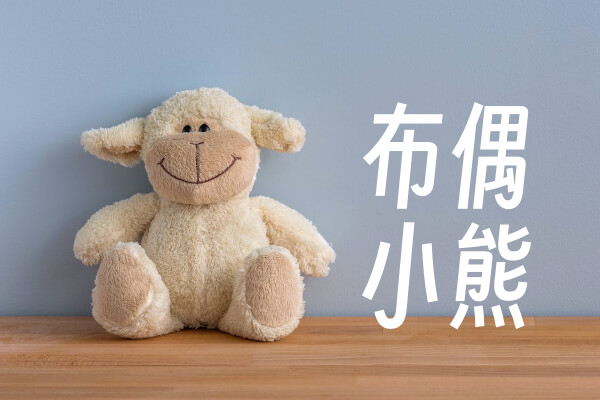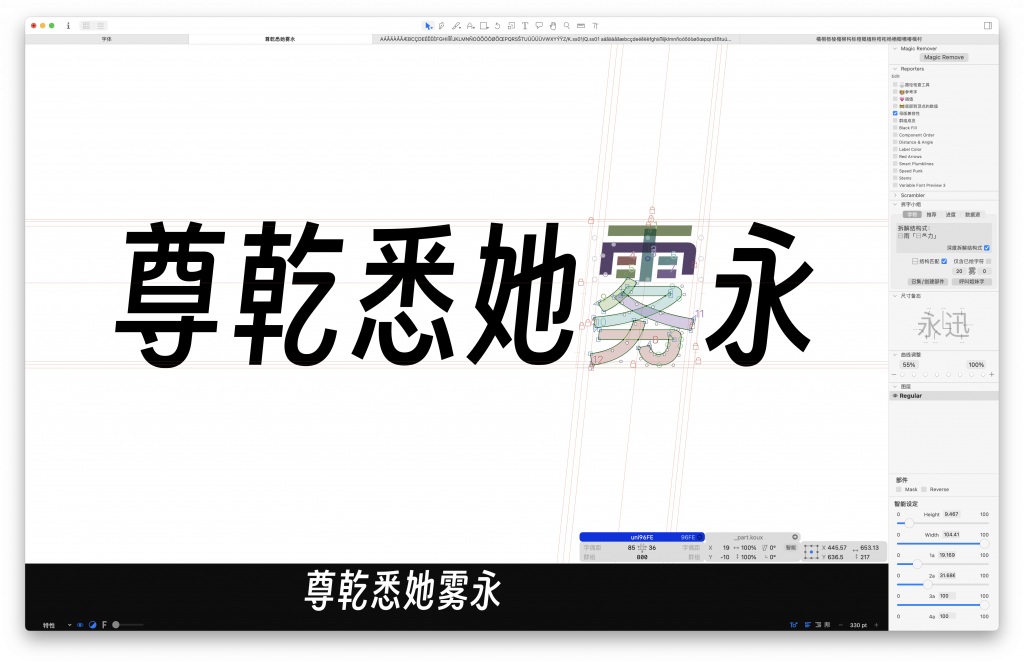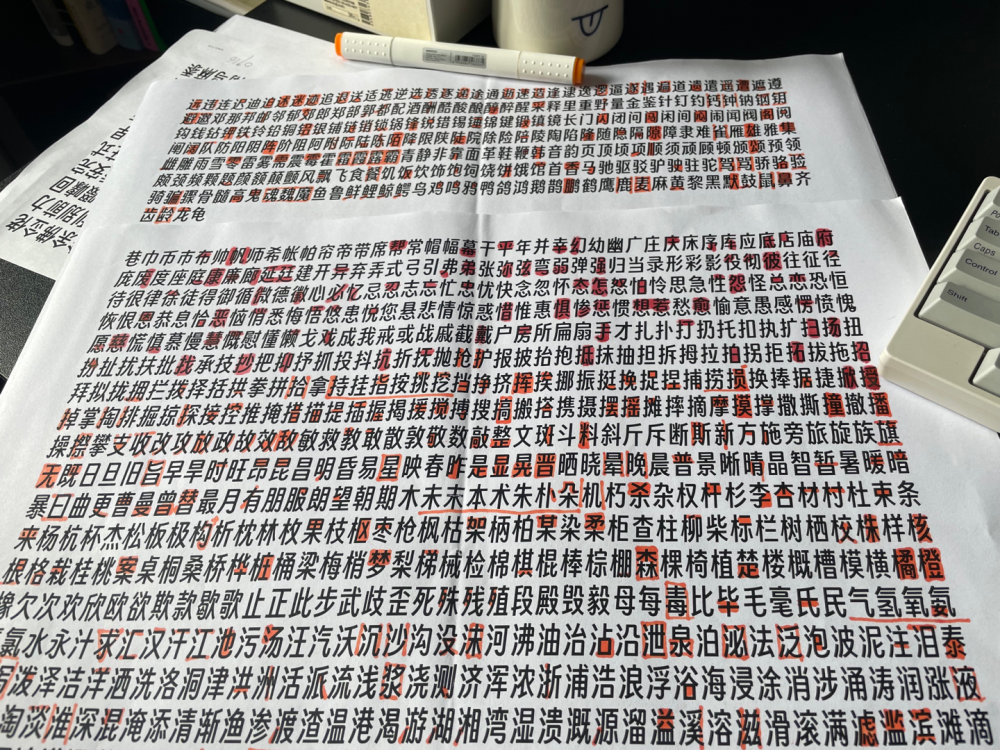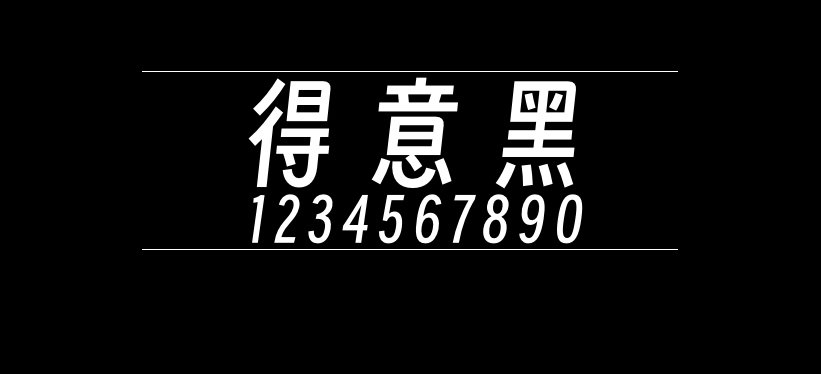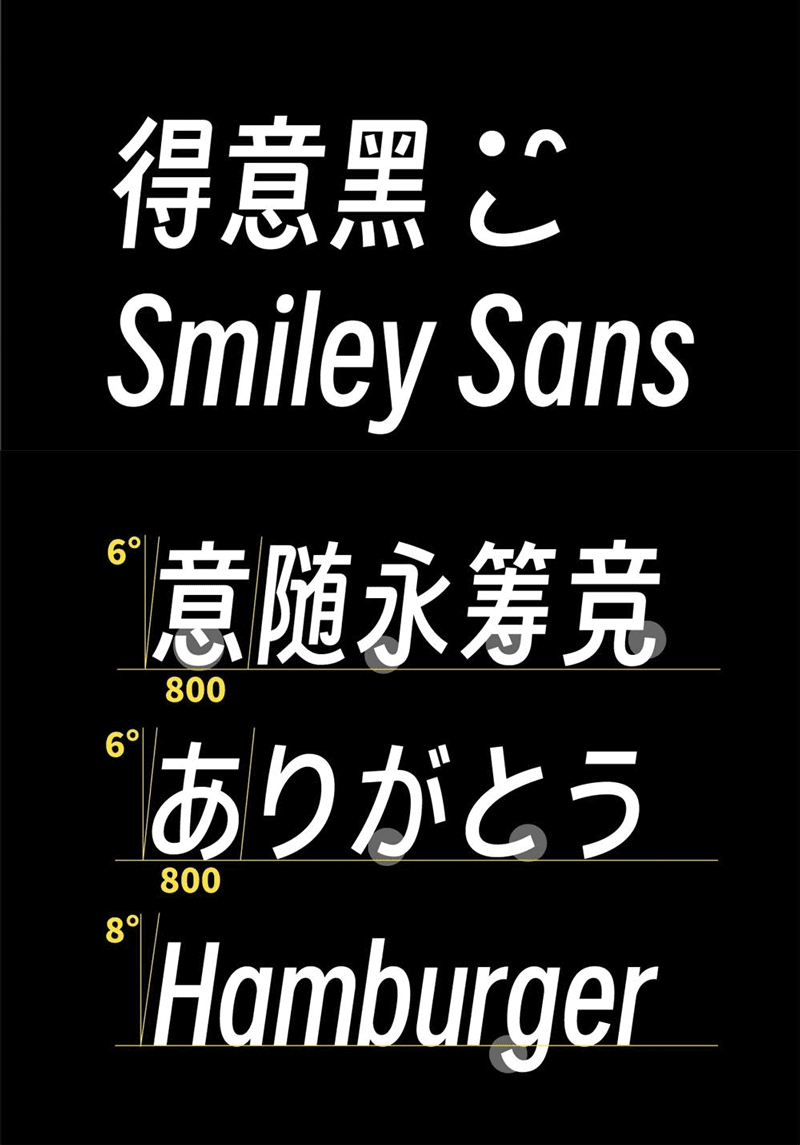
得意黑
得意黑(Smiley Sans)是oooooohmygosh发布的第一款字体,11月15日正式开源发布,大家可以免费商用无任何限制,也可以修改创作。作者希望以这个身份发布的所有作品,都是开源或者公益的。 这套字经过作者和其他字体设计师伙伴们一年多的波折,终于要面世了。据作者介绍,这款字虽然是美术字,但却是一个有挑战的命题。因为它有三个特征「大弧线、窄、斜」,每一项都很难做好。更何况把它们仨融合到了一起,还要去追求稳、匀、整……
得意黑是一款在人文观感和几何特征中寻找平衡的中文黑体。整体字身窄而斜,细节融入了取法手绘美术字的特殊造型。字体支持简体中文常用字(覆盖 GB 2312 编码字符集)、拉丁字母、日文假名、阿拉伯数字和各类标点符号。
字符集支持
汉字(中国大陆)
字体覆盖 GB 2312 编码字符集中的全部 6763 个汉字,并额外补充了 啰、喰、瞭、 4 个字,共计支持汉字 6767 个。
拉丁字母
除基础拉丁字母外,覆盖欧洲、美洲、南亚各种语言所需的字符共 415 个,另加入必要的变体和本地化字形,可支持 100 余种语言,包括英语、法语、德语、西班牙语、芬兰语、越南语等等。
日文假名
支持平假名、片假名字符共 174 个。
数字及标点符号
支持阿拉伯数字、大小写罗马数字,以及其他 4 种样式的序数字 ㈠、②、⑶ 和 ⒋。标点符号和其他各类符号共 200 余个。
本字体部分笔画和结构采用了美术字风格的形态处理方式,并未严格遵循中国大陆规范汉字写法,敬请注意。
使用场景:
推荐:平面海报、电商文案、视频字幕、书报标题、游戏嵌入等;
不推荐:正文排版、编程代码、手机界面等。
得意黑效果预览